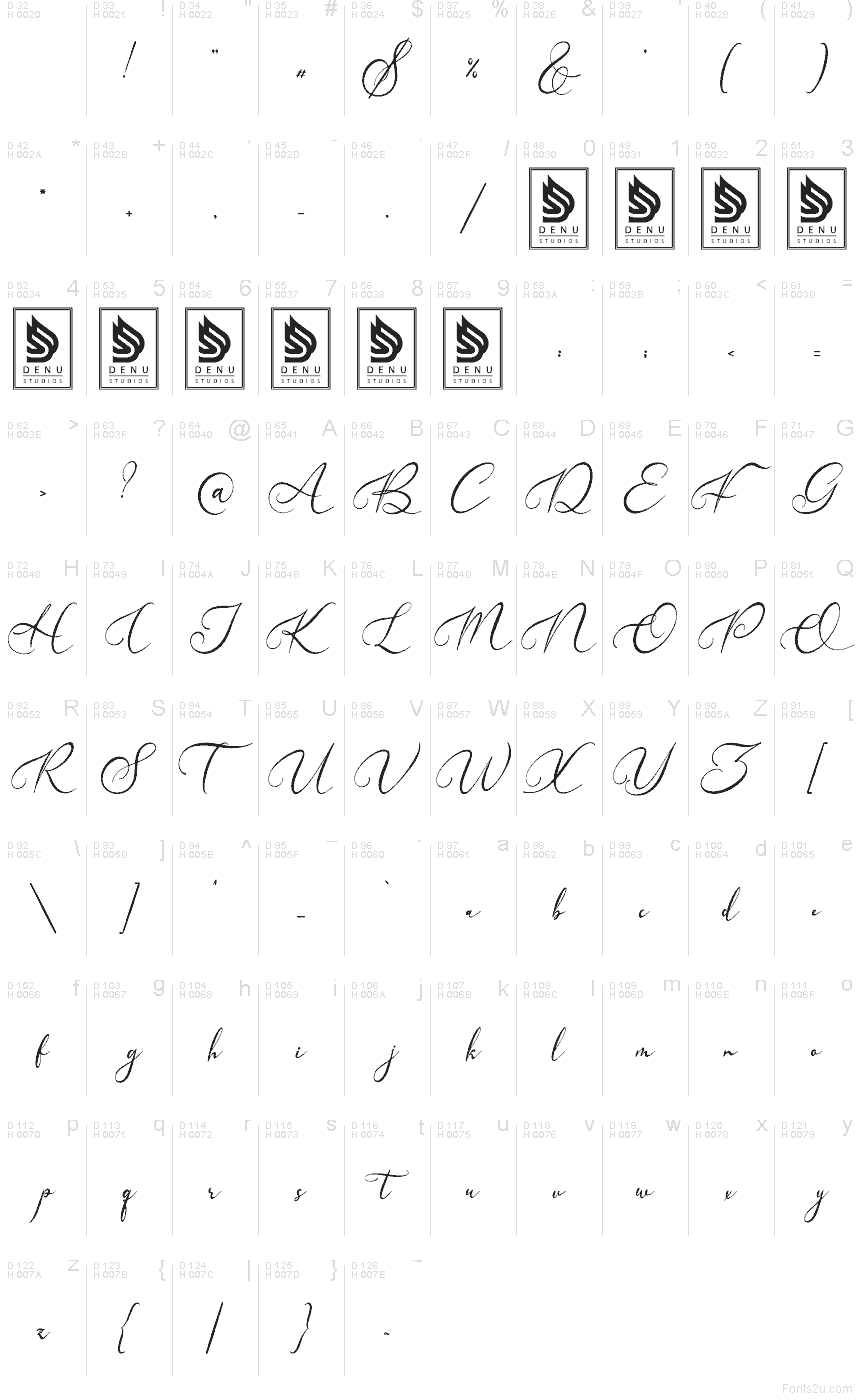
Velocity Romantica de Denustudios es una tipografía caligráfica romántica gratuita, definida por sus largos trazos iniciales y letras inclinadas que se sienten naturales y manuscritas, lejos de la rigidez formal. Su ritmo nace del contraste entre los remates amplios y unos trazos finales muy ligeros, lo que le confiere a este diseño una calidez íntima y elegante.
Es ideal para invitaciones de boda, branding de belleza, packaging boutique, portadas y títulos en redes sociales donde se busque dinamismo visual. Al ser una tipografía gratuita, funciona especialmente bien en textos cortos, firmas y monogramas, aportando a cada palabra un toque personal gracias a sus delicadas conexiones y trazos fluidos.